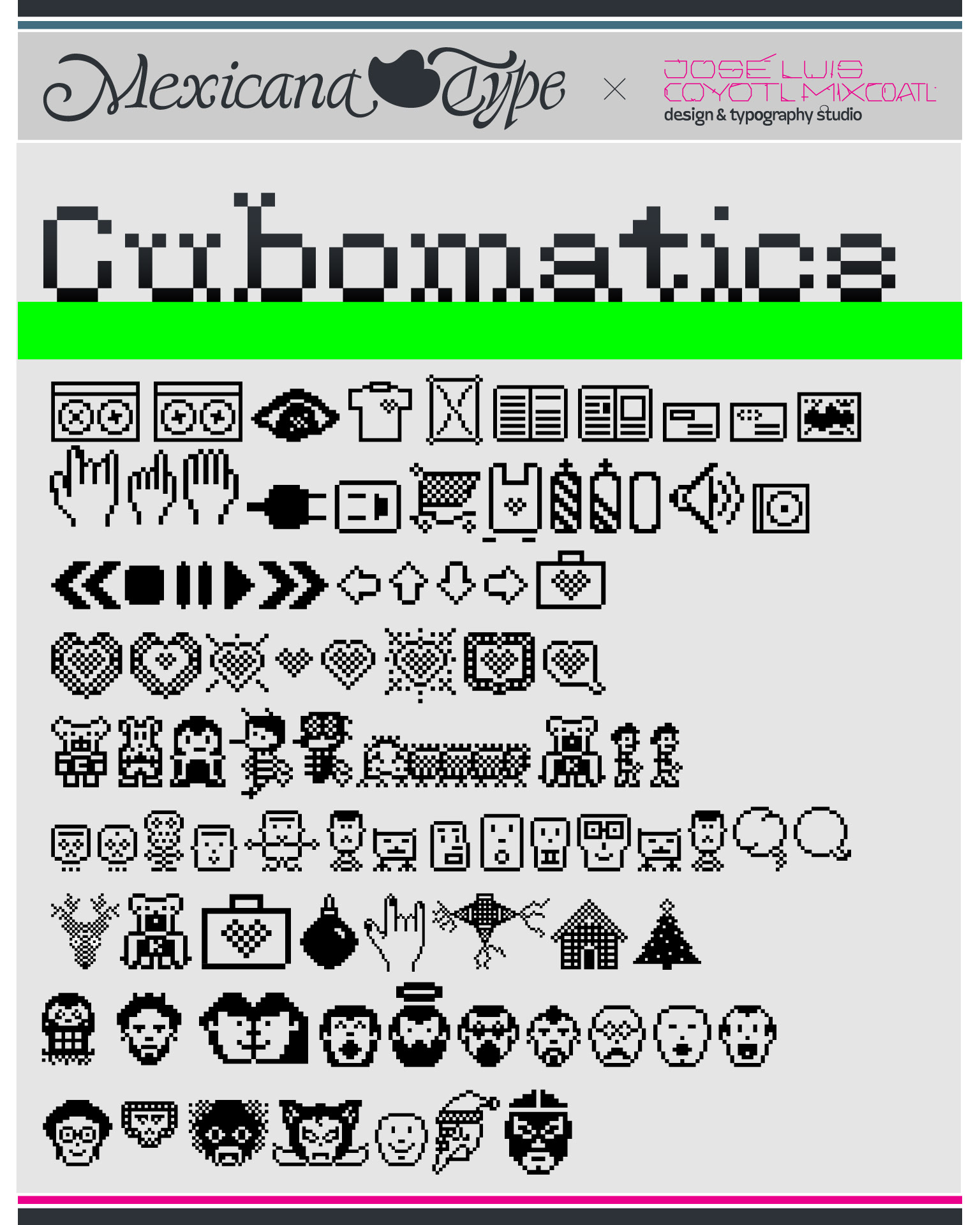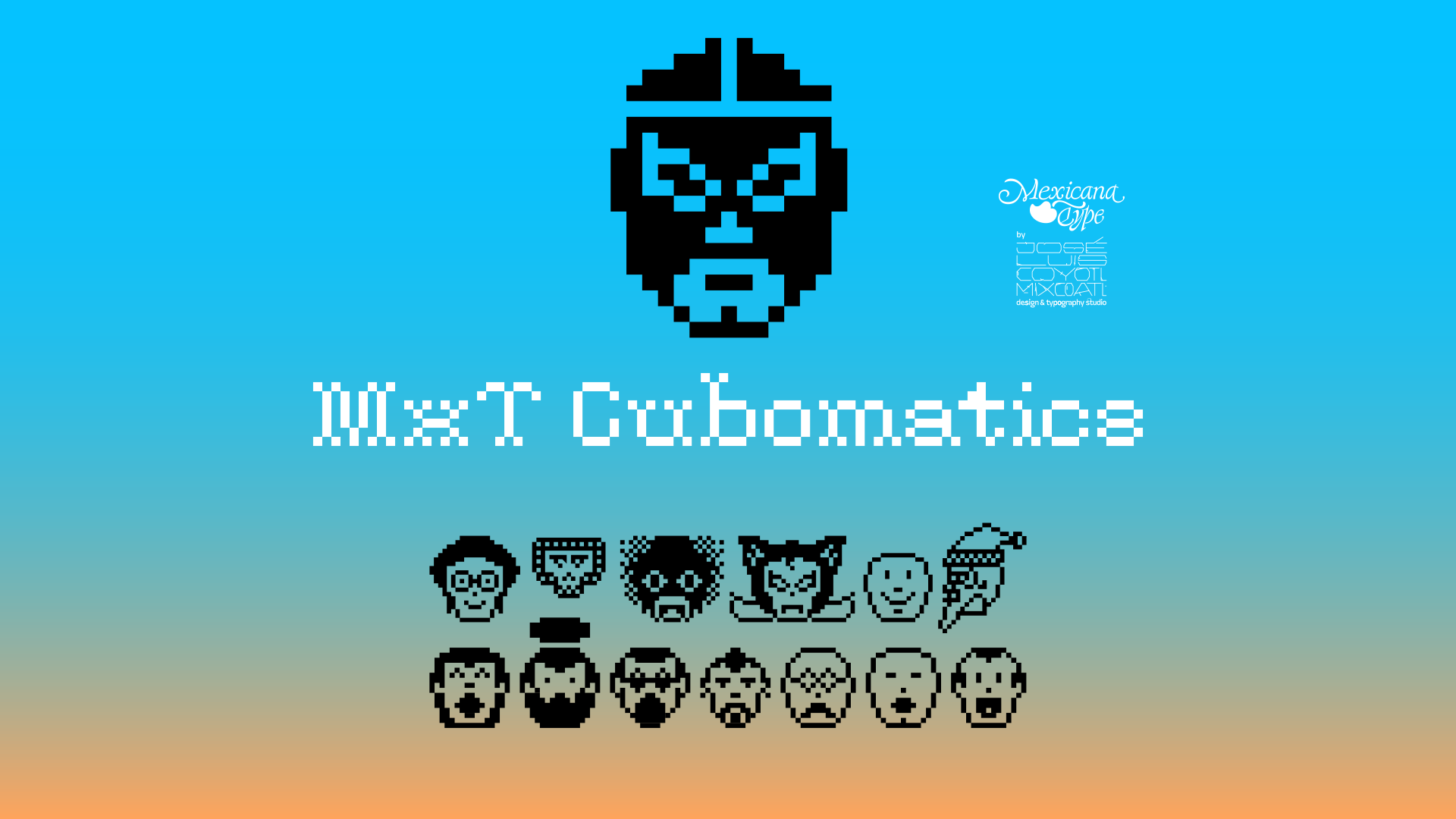
MxT Cubomatics fue una colección de íconos diseñados para la interface de mi sitio de internet y mi marca personal a mediados de la primera década del 2000, con la intención de tener una serie de elementos con una estética de 8 bits monocromática, tanto para íconos de secciones del sitio, cursores y otros elementos de uso promocional para materiales impresos, permitiendo un uso muy lúdico al ser de uso personal.